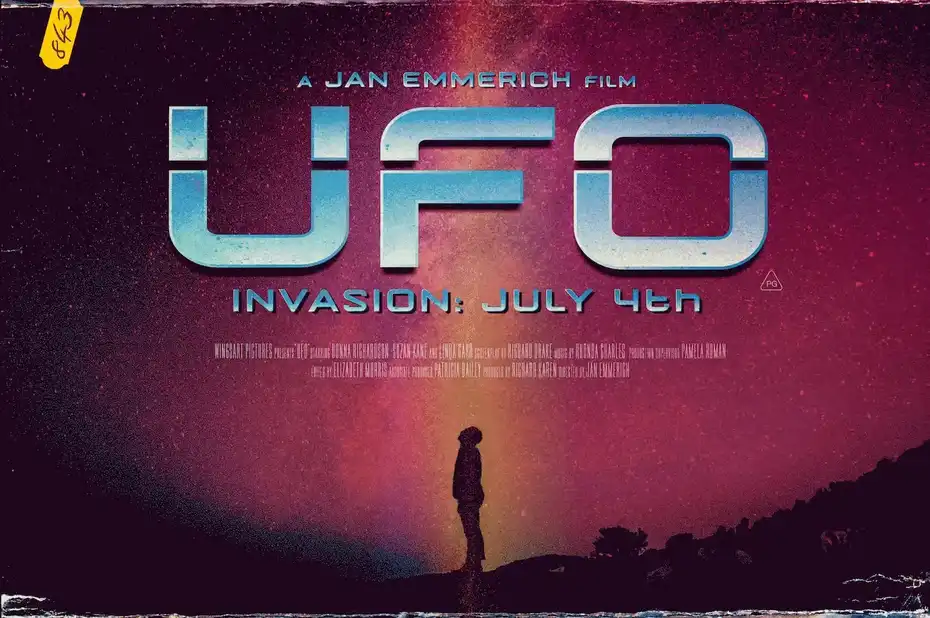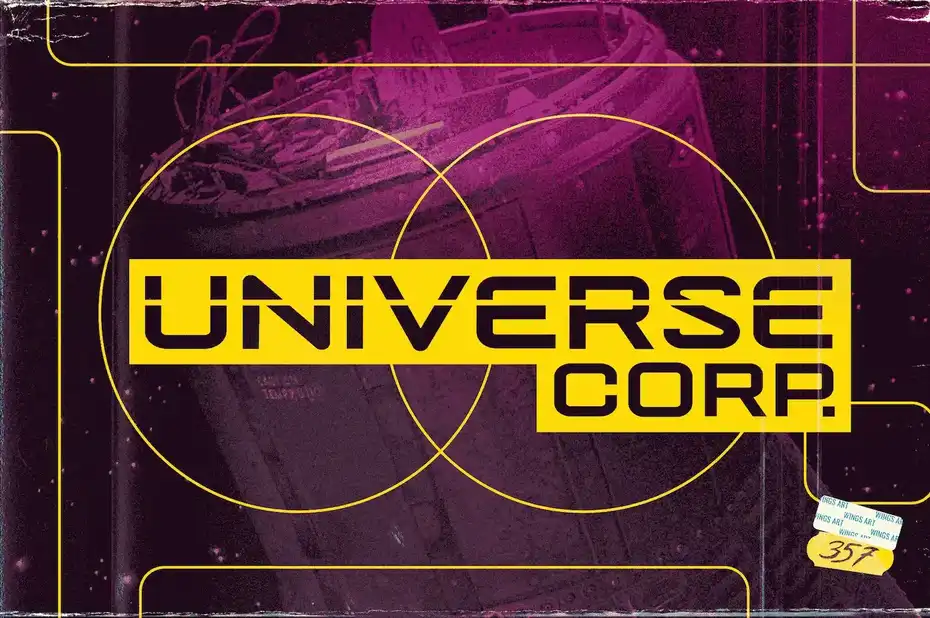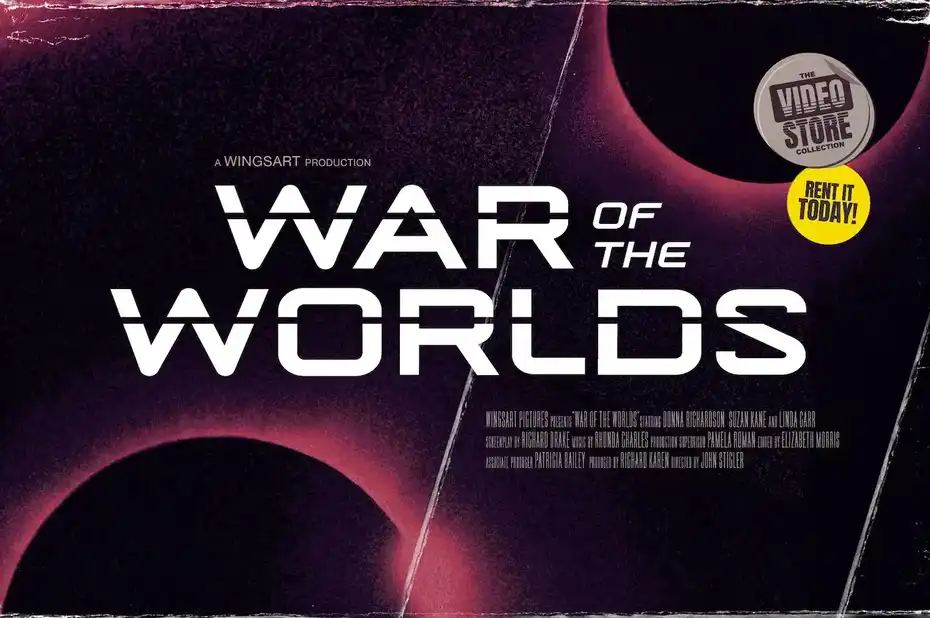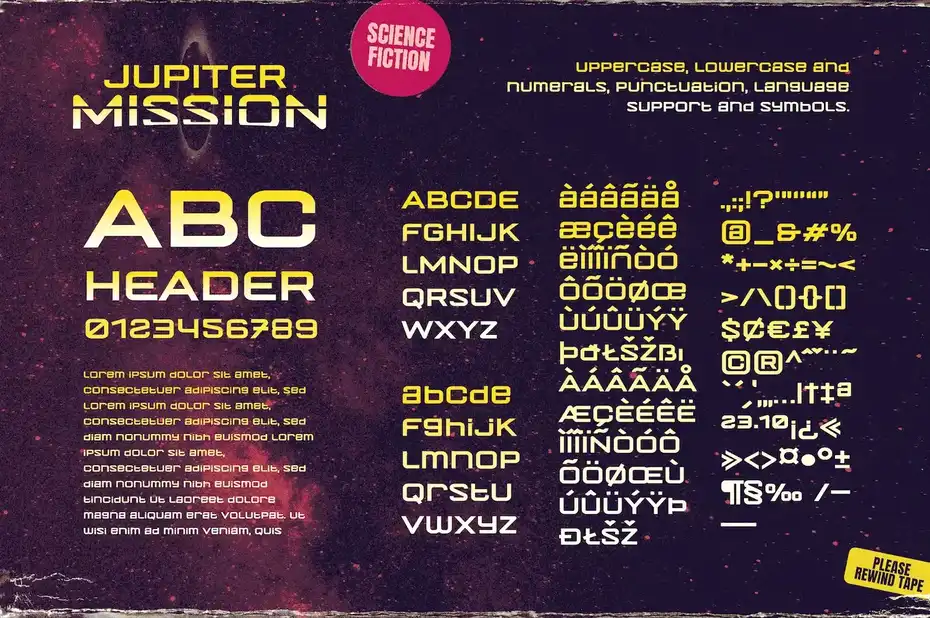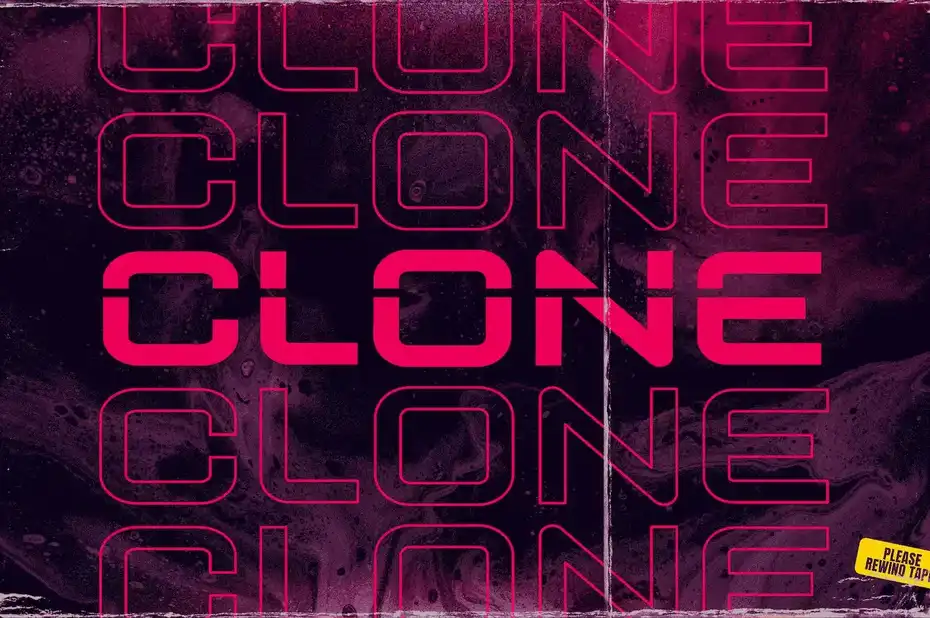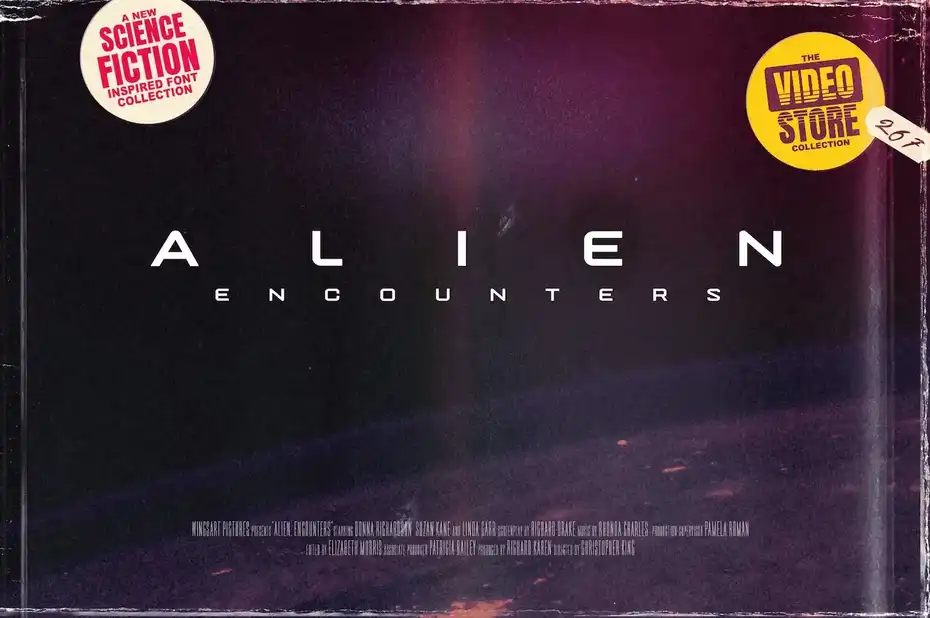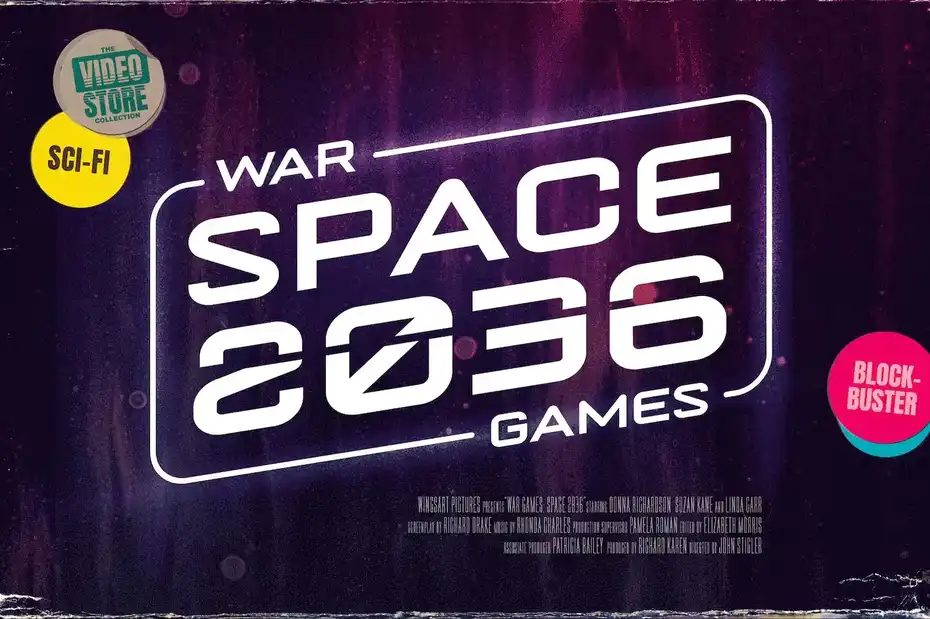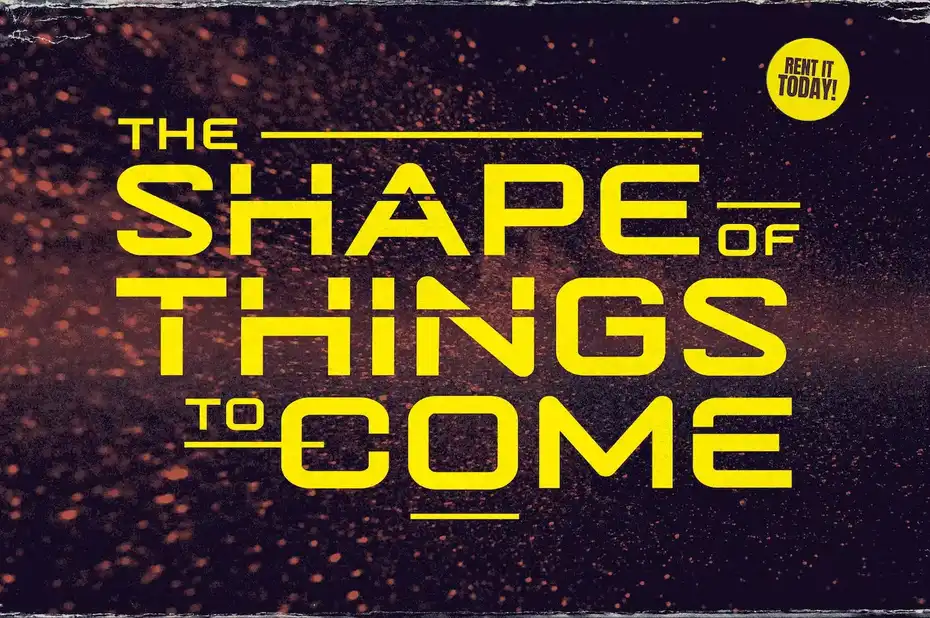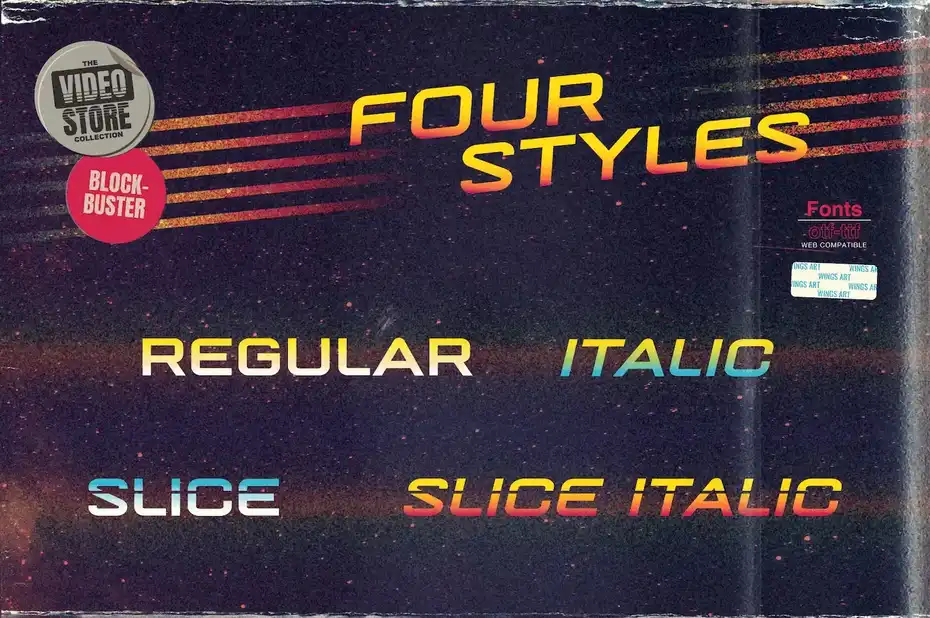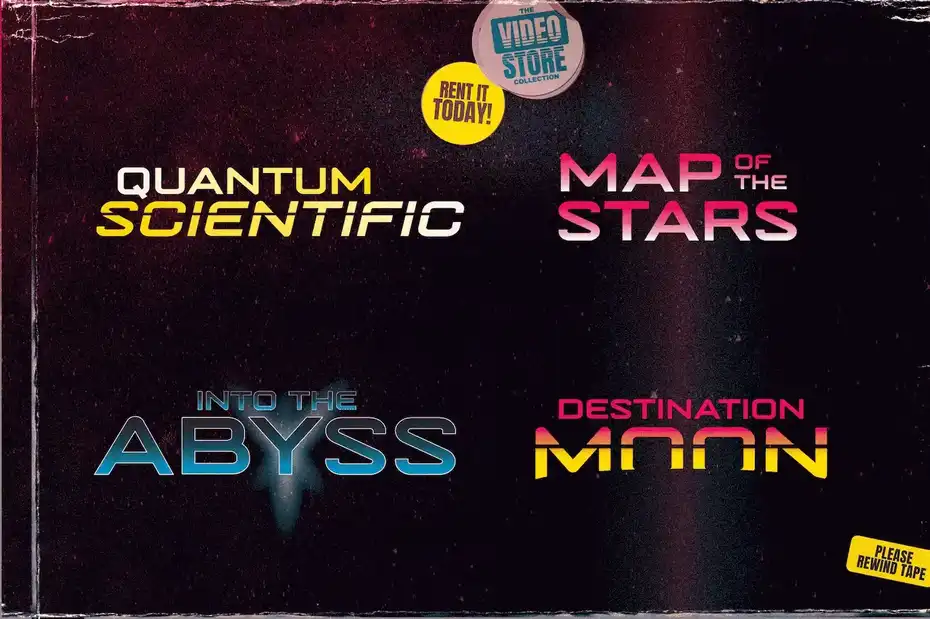
دانلود فونت انگلیسی Jupiter Mission A Science-Fiction Font
فونت انگلیسی Jupiter Mission A Science-Fiction Font : این مجموعه شامل یک فونت فانتزی است که برای عناوین فیلم‌ های علمی تخیلی، عناصر طراحی تولید، مقالات فناوری، بازی‌ های ویدیویی و غیره مناسب میباشد.
• سبک: Sans-Serif